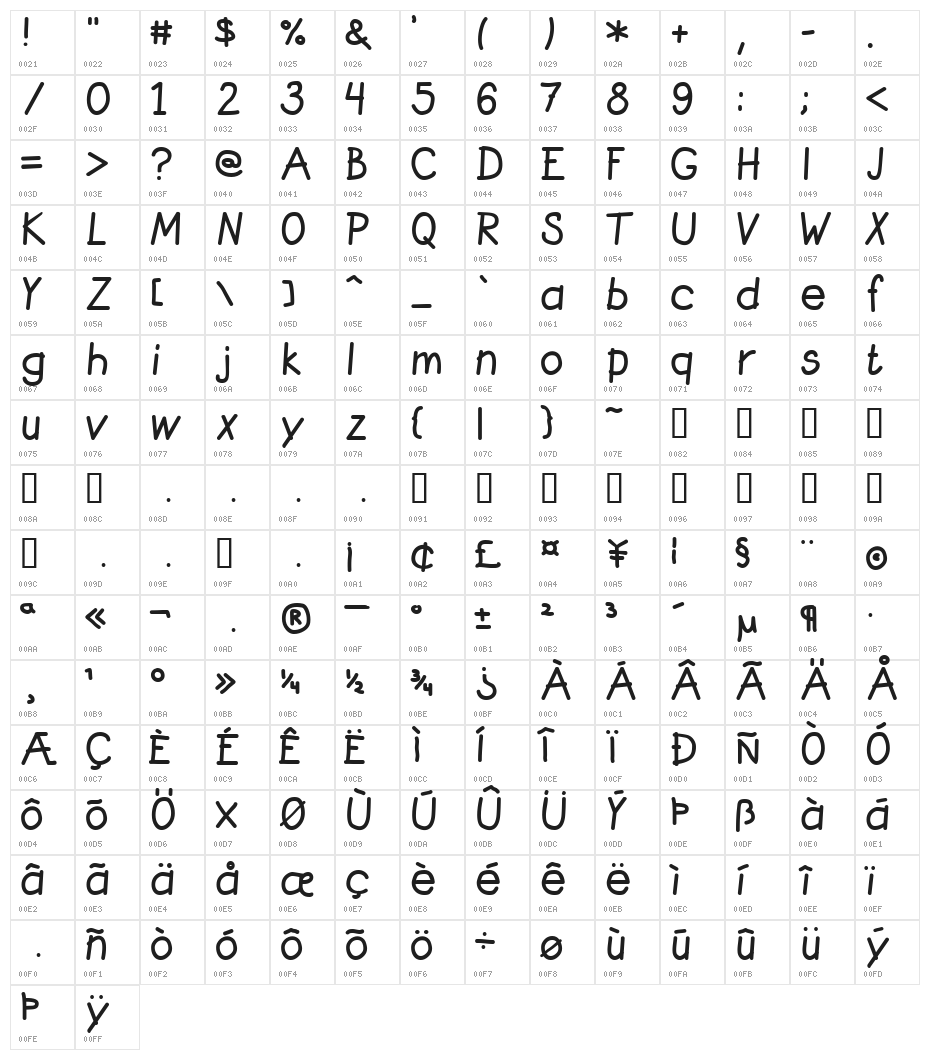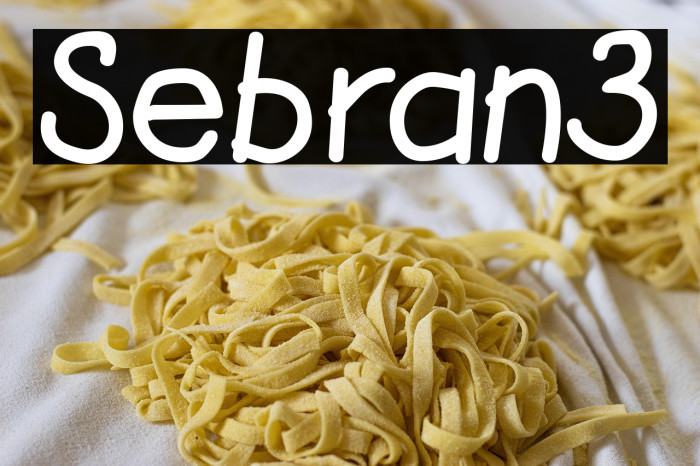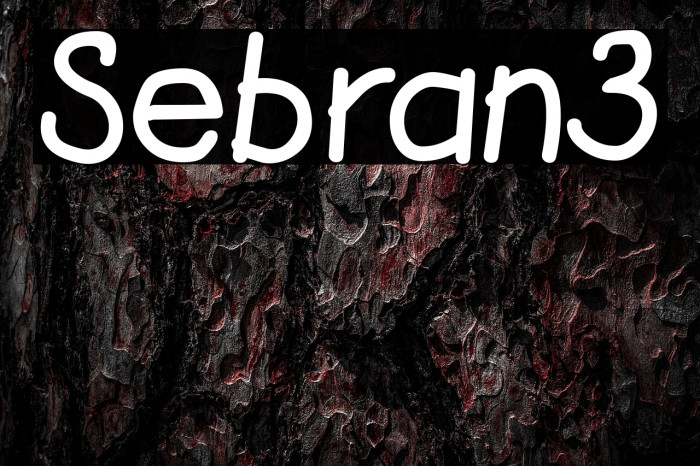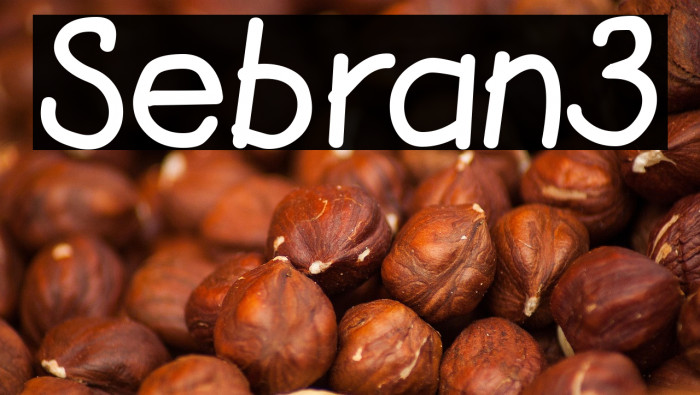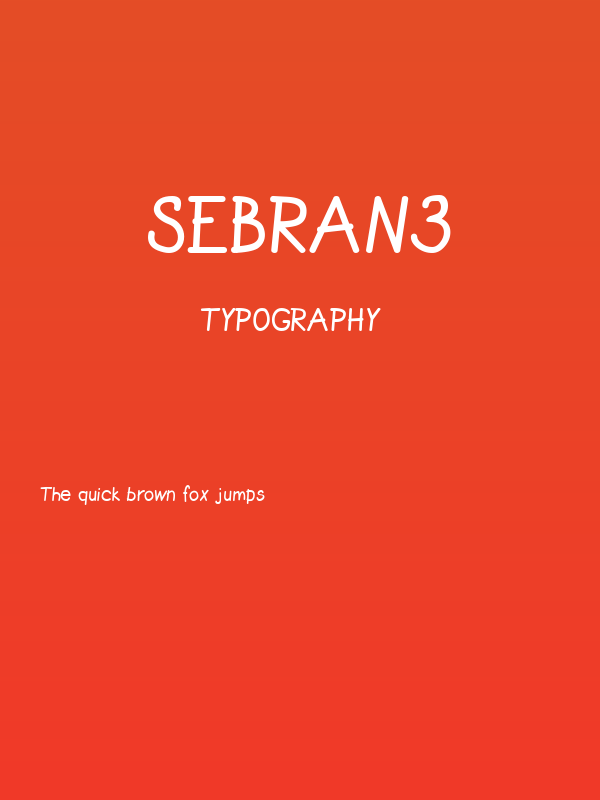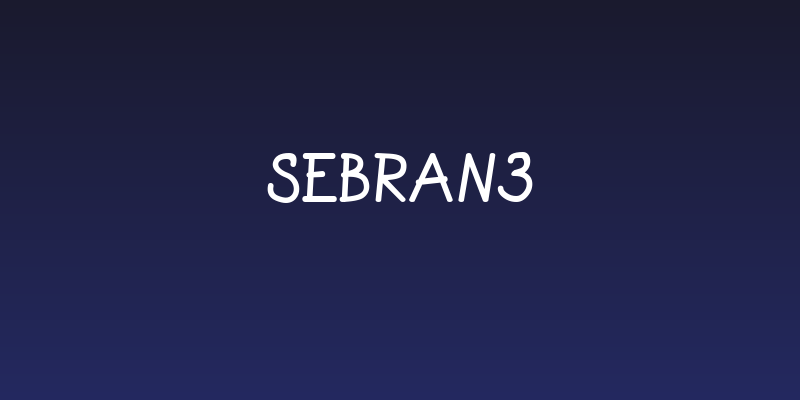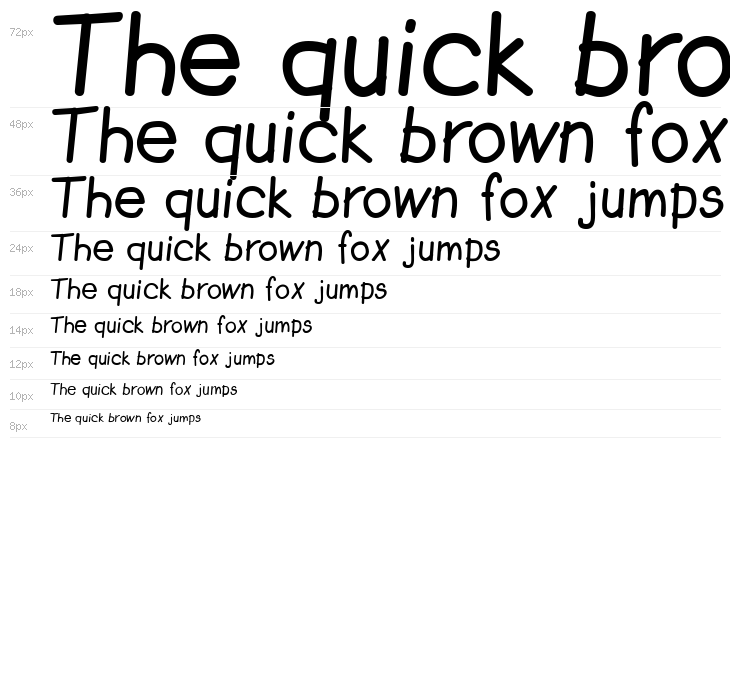
Sebran3 Font
| Gesamtstil | Casual, Friendly |
| Anwendungsfall | Headlines, Informal text, Educational materials |
| Vorgeschlagene Projekte | Children's books, informal invitations, educational materials. |